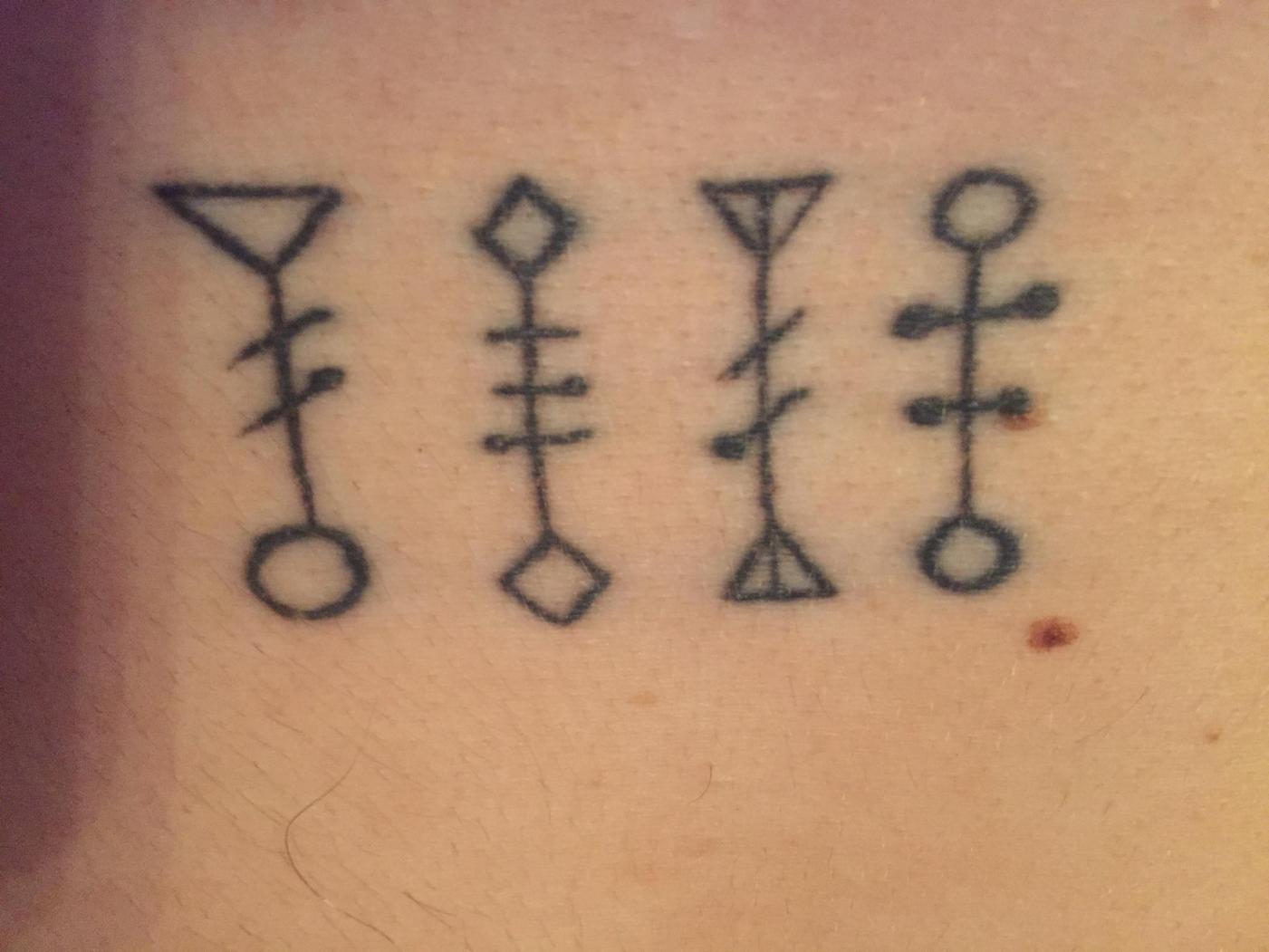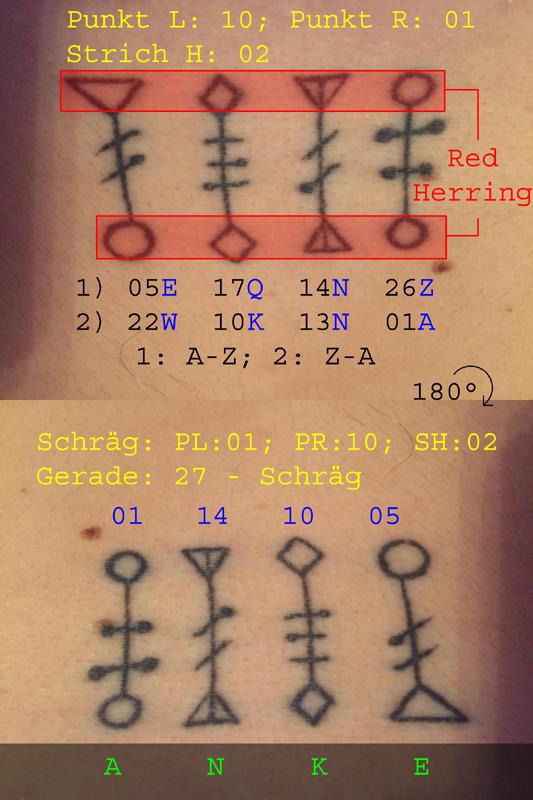
Suche 4 Symbole
Hallo alle zusammen ich suche 4 Symbole würde gerne wissen ob diese jemand kennt oder gesehen hat da ich leider keine Ahnung habe was sie bedeuten und wo sie her kommen.
Die Chancen, dass jemand deine Frage beantwortet, dürften steigen, wenn du uns etwas Kontext lieferst, etwa, wie du auf diese Zeichen gestoßen bist. Immerhin postest du hier ja das Bild eines Tattoos (und normalerweise weiß die Person, die sowas trägt, ja ungefähr, was sie sich stechen lässt). Woher kommt das Bild?
Wäre es kein Tattoo, würde ich ja vermuten, es handele sich um Teile einer Reihe von Grafikanalogien aus einem Intelligenz- oder Logiktest. Also sowas wie hier ab Frage 16.
Wilde Spekulation:
Scheint die Haut einer Frau zu sein. Wo wurde tätowiert! Im Bereich unterhalb des Bauchnabels? Die Schatten links irritieren. Dreimal gleichförmig sich überlagernd...
Wurden die Zeichen gleichzeitig oder nacheinander tätowiert? Das Erste ist vom Duktus deutlich freizügiger. Aber auch die anderen Zeichen unterscheiden sich deutlich, beispielsweise in den Punkten.
Mir kam der indiskrete Gedanke auf: stammt das von deiner Freundin...:-)  Jedenfalls ist das polare Element in den Zeichen sehr deutlich. Dabei sind immer Querstriche in den Verbindungen. Die schrägen sehen eher schmerzhaft aus. Eine Reihe bisheriger Liebesbeziehungen? Das vierte sieht schon sehr harmonisch aus. Spannend wäre, wie das fünfte aussähe und ob dann nochmal ein sechtes kommen könnte?
Auch wenn eine Neigung zum kosmologischen zu vermuten wäre, den Muttermalen wurde dergleichen nicht zubemessen. Jedenfalls scheinen jene nicht beachtet worden zu sein.
Wie gesagt, alles rein spekulativ. Diese Bild regt aber irgendwie zur Spekulation an.
Ist auf meinem Körper tattowiert und es gibt noch weitere aber noch nicht gestochen ich weiß nicht was sie bedeuten und kann auch nicht wirklich rational erklären wie ich da ran gekommen bin vielleicht bin ich auch einfach nur verrückt 🙌🏻 Im Internet ist absolut nicht darüber zu finden
Hm, dann waren es wohl Außerirdische? Die sind m.W. allerdings nicht hier im Forum aktiv ... Vielleicht tätowieren sie dir ja bei Gelegenheit die Auflösung. Bitte berichten!
In welcher Weise kannst du es denn erklären? Irgendeine Quelle muss es ja geben.
Wonach hast du denn gesucht? Ohne Kontext wüsste ich auch keine Suchphrase. »Komische Symbole, die ich mir habe tätowieren lassen« wird freilich nichts bringen. ;-)
Na ja, es gibt ja auch Menschen, die unfreiwillig an Tattoos geraten sind …
Aber mal von diesen Spekulationen weg und hin zu den Zeichen – das erinnert doch wieder an diverse Geheimschriften, so etwas wie die „Tanzenden Männchen“ von Conan Doyle … :-?
Du hast Dir im bewusstseinsgetrübten Moment eine "Geheimschrift" tätowieren lassen. Vier Zeichen sind -- es sei denn, Du hast eine Idee, wofür vier unterschiedliche Zeichen stehen könnten wie Geburtsjahr oder Name -- nicht ausreichend, um die Ersetzung zu dechiffrieren. Daraus folgt für mich: völlig Banane, was es bedeuten sollte, denk Dir einfach eine lustige Geschichte dazu aus und bleib bei der.
Coole Idee! Einfach eine komplette Schrift dazu ausdenken und folgerichtig weiterschreiben. Vielleicht heißt das ja YOBI? ;-)
Das war übrigens mein erster Versuch da eine mögliche Bedeutung zu finden. Ich habe ähnliche Konstruktionsprinzipien mit einem (oder mehreren Senkrechten) und einer Anzahl waagrechter Striche schon mal gesehen. Allerdings kam ich da bei einer Dreierteilung des Alphabets nicht zum Ziel, der letzte Buchstabe ging schief. Aber man kan es ja noch mal versuchen. Vielleicht habe ich ja einen Fehler gemacht?
Fange mit dem B an ... zwei Striche ... also hätte das A einen Strich ... der Stamm wäre dann für den ersten Stamm ... Dann probiere weitere Stämme so zu setzen, dass die Buchstaben Y, O und I jeweils die Zahl der Stricke dahinter sind ...
Du hattest bei der Tattoo-Auswahl eindeutig, bewusst oder unbewusst, eine Anke im Sinn! 😄
Anke? Wer ist Anke? Betrachte den Roten Herring doch als Anker? Damit das erste Zeichen ein Y ist und die zwei Balken den Sprung minus 1 vom Anker angeben wäre der Anker dann bei X. Bei O dann M ... Und bei B ... A? I ... H ... Haben die manchmal vorhandenen Punkt am Ende der Striche eine Bedeutung? Und dann noch eine nette Verschwörungstheorie über die Nummerierung von Bucheinbänden der Freimaurer ... und fertig ist eine impoposante Geschichte. *fiesgrins*
P.S.: Ehrlich gesagt habe ich mich mit großer Wahrscheinlichkeit verrechnet, war schon sehr müde gestern. 😬
Die Frage steht hier vielleicht im falschen Forum. Wenn jemand rausbekommt was das heißt, dann die Leute in Klausis Krypto Kolumne:
Viel Spaß allen, die das noch nicht kennen!